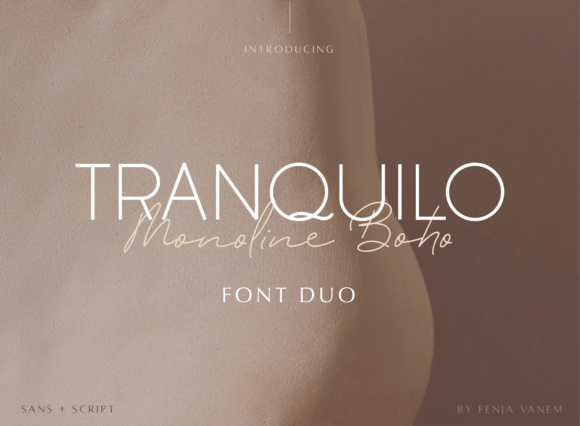
Tranquilo Monoline Boho
Doğru tasarım öğelerini bulmak zor olabilir, ancak Tranquilo Monoline Boho, çalışmanızı anında bir üst seviyeye taşıyan olağanüstü bir koleksiyon sunar.
İster İsteğe Bağlı Baskı (POD) ürünleri, ister düğün davetiyeleri veya sosyal medya grafikleri oluşturuyor olun, Tranquilo Monoline Boho ideal bir uyumdur.